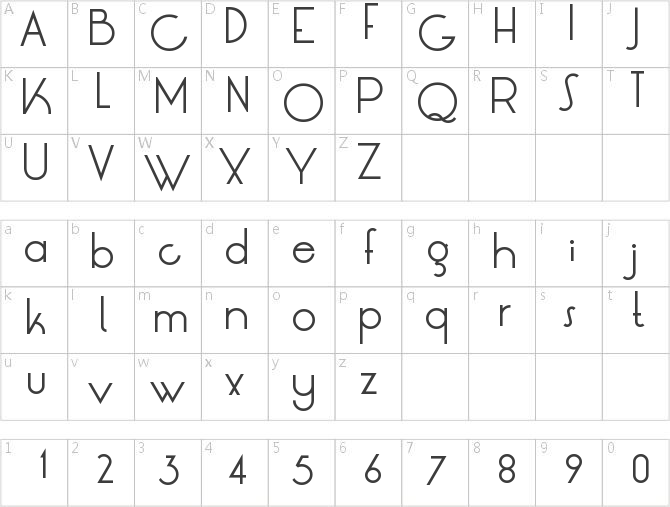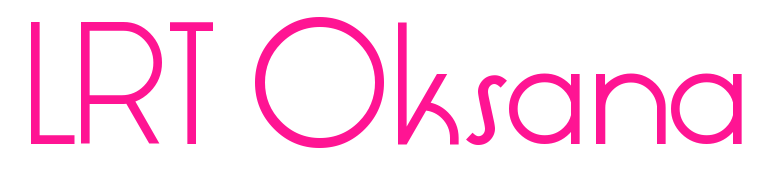
LRT Oksana 詳情頁(yè)
字體名稱: LRT Oks
LRT Oksana
LRT Oksana字體字庫(kù)是一款讓人賞心悅目、百看不厭的英文字體,適合各類廣告和產(chǎn)品包裝設(shè)計(jì)應(yīng)用,字體大小0.08MB,格式為ttf字體,上傳用戶是小籃子,作者/版權(quán)方為未知